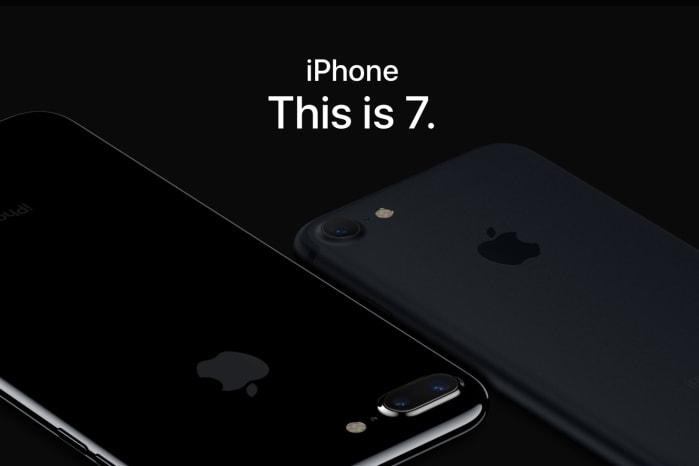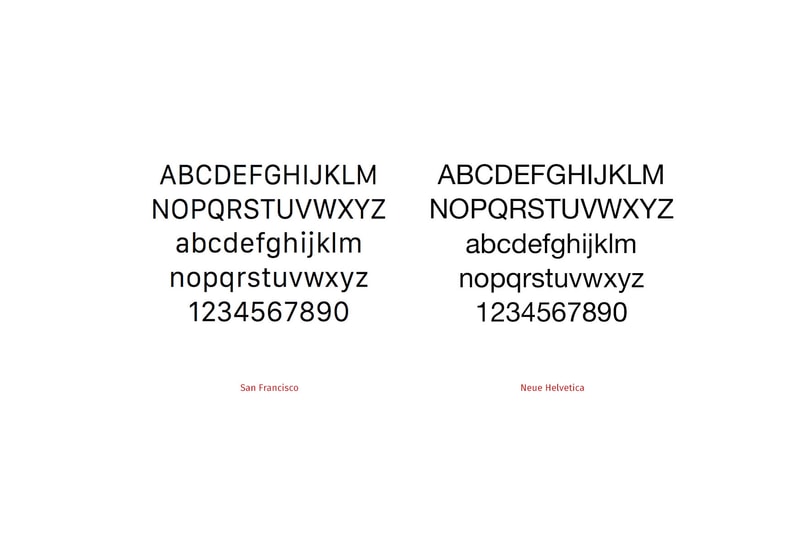
簡潔鮮明- Apple 官網正式採用自家字體 San Francisco
就連字體都要用上自家製的才十全十美。
設計學裡頭,總是會聽到說 「Less Is More」,即是簡單就是美,近年頭亦興起了簡約這一詞,字體來說普通人未必會發覺的轉變,在設計師眼中 Typeface 是何其重要的細節。而 Apple 就剛剛正式為其官方網頁換上了自家設計的 San Francisco 字體,這字體是蘋果於 2014 年發佈,用作為 Apple Watch 系統所用,亦是公司近 20 年來設計的第一款新字體,最先出現的自家設計字體是在 80 年代時找來設計師 Susan Kare 為他們設計,之後都是一直替換既有成的字體如 Lucida Grande、 Helvetica Neue Light 及 Helvetica Neue。而 San Francisco 是蘋果花了很多心思在螢幕上的辨讀性而設計出來,取代了 Helvetica Neue,就這樣看其實分別不大,但細心一看就會發現兩者之間相比, San Francisco 可自行適應間距和行高,能夠在不同大小螢幕下作出調整,都市人幾乎每日都要注目在智能裝置上,此舉絕對能讓各位雙眼看得舒服一點。